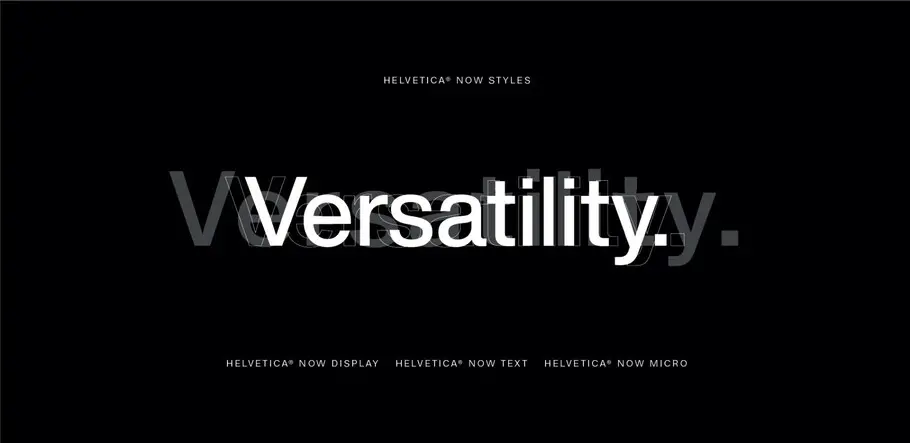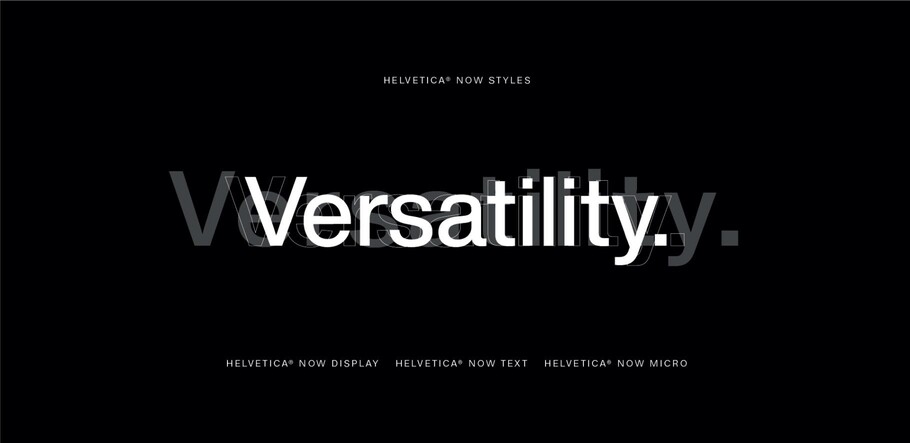
Was sind optische Größen und warum sind sie heute so wichtig?
Eine der jüngsten Neuheiten aus dem Monotype Studio, Helvetica® Now, bietet die drei optische Größen Mikro, Text und Display, wodurch sich die Einsatzmöglichkeiten von Helvetica dramatisch erweitern. Optische Größen waren zu Zeiten des Bleisatz praktisch Standard, gerieten aber in den ersten beiden Jahrzehnte des digitalen Schriftdesigns fast in Vergessenheit. So ist es kein Wunder, dass diese nützliche Technik selbst Designprofis kaum bekannt ist.
Situationsspezifische Typografie
Als „Optische Größen“ bezeichnet man im Typedesign die Praxis, Schriftzeichen für definierte Textgrößenbereiche unterschiedlich zu gestalten. Tatsächlich erleben wir eine Helvetica-Schlagzeile auf einem Großflächenplakat anders, als auf dem Smartphone oder in einer Zeitungsspalte. Die optische Anpassung einer Schrift für unterschiedliche Textgrößen kompensiert Wahrnehmungsunterschiede, zum Beispiel mit Änderungen beim Strichstärkenkontrast und beim Zeichenabstand. Lange Zeit war es üblich, Schriften in einer optischen Kompromissgröße zu entwerfen (Single Master) und zu hoffen, dass sie über alle Textgrößen gut lesbar funktioniert.
The optical sizes in Helvetia Now enable it to unction flawlessly in a range of applications, from large, eye-catching display text to hyper-legible micro type.
Bei der Neuveröffentlichung der klassischen Serif-Familie Walbaum fürs digitale Zeitalter, malte Monotypes Design Director Charles Nix folgendes Bild: „Stellen wir uns mal vor, dass die Proportionen 10-Jähriger als die perfekte menschliche Form definiert würden, und Babys wie verkleinerte Teenager aussähen und Erwachsene wie deren Vergrößerung. Babys sind aber zum Glück keine Miniaturen 10-Jähriger, und so sollte eine 5-Punkt-Schrift auch keine Verkleinerung einer 12-Punkt-Schrift sein.“
In der Zeit vor dem Type-Design am Computer passten die Schriftgestalter ihre Entwürfe für jede Größe einer Schrift an, um stets die beste Lesbarkeit zu erzielen. Kleinere Schriftgrade erforderten größere Buchstaben-Innenräume und mehr Zeichenabstand. Groß gesetzte Headlines dagegen profitieren von Buchstabenkontrast und -details. Als die ersten Schriften am Computer entstanden, setzte sich die praktische Single-Master-Methode, und One-Size-Fits-All wurde zur Norm.
Was ist normal?
Weil wir wissen, dass es die Größe für alles nicht gibt, überarbeiten und entwerfen immer mehr Schriftenhäuser ihre Fonts mit größenabhängigen Feinheiten, um die Makellosigkeit eines Text-Designs zu erhalten.
Obwohl es bei der Gestaltung und der Beurteilung von Schrift vor allem um deren Form(en) geht, bewege sich die Konzeption optischer Größen zwischen Kunst und Wissenschaft, betont Nix.
„Es erfordert nicht nur unsere Sensibilität für Formen und Zwischenräume“, sagt er. „Verbesserungen werden erst durch Beobachtung, Hypothesen und Experimente erreicht. Es geht um Studieren, Probieren und Verfeinern – ein iterativer Designprozess.“
Für Nix stehen ganz am Anfang Fragen: „Was ist eigentlich normal? Ich frage mich das jedes Mal, wenn ich eine Schrift mit optischen Größen entwerfe. Es klingt nach einer existenziellen Krise, denn Designs für sehr kleine Texte müssen den gleichen Eindruck wie bei normaler Textgröße ergeben. Und Entwürfe für größere Größen müssen das Normale so verfeinern, dass sie der Überprüfung durch eine Großaufnahme standhalten. Was ist normal? Es ist die Essenz dessen, was Design erreichen möchte – sein Ethos.“
Bei der Überarbeitung der Helvetica, einer vor über 60 Jahren veröffentlichten Familie, blieb das Monotype-Team der ursprünglichen Absicht treu: eine Schrift, die Klarheit, Einfachheit und Neutralität bietet. Das Ergebnis, Helvetica Now, ist eine für die heutigen Bedürfnisse angepasste Helvetica. Die Familie besteht aus 48 Schriften mit den drei optischen Größen Display, Text und Micro, die auf kleinen und großen Bildschirmen genau so überzeugen wie im Klein- und Großgedruckten. Oder wie Nix sagt: „Sie funktioniert einfach, in allen Anwendungsbereichen: von der überdimensionalen Fassadenwerbung in der City bis hin zum Mikrotext auf unseren Smartphones.“
Auch die Display-Schnitte, gedacht für Punktgrößen über 14, wurden neu gezeichnet, wobei die Feinheiten in den Buchstaben erhalten blieben und  deren Spationierung für Headlines optimiert wurde. Die Text-Version, gedacht für 8 bis 12 Punkt, wurde so optimiert, dass sie den Anforderungen an die Lesbarkeit von Mengentext gerecht wird. Die Striche sind robust, der Kontrast reduziert und die Abstände luftig, was zu einem angenehmen Lesen führt. Die Palette der Strichstärken erlaubt feinstes Informations- und Editorial-Design.
Die Mikro eignet sich für Kleingedrucktes zwischen 3 und 7 Punkt, sowohl auf Papier als auch für Retina-Screens. Die Lettern sind vereinfacht und übertrieben gestaltet, um das Gefühl von „Helvetica“ zu bewahren; der Zeichenabstand ist extrem großzügig – ein wesentliches Merkmal für hyperlesbare Mikrotexte.
Warum das wichtig für Marken ist
Optische Größen schaffen ein besseres Nutzererlebnis, erleichtern das Lesen und Verstehen und sorgen für Vielseitigkeit, Zugänglichkeit und Flexibilität. Dies ermöglicht es Marken, schnell und effektiv mit ihrem Publikum in einer unbegrenzten Bandbreite von Medien zu kommunizieren, ohne ihre visuelle Identität zu untergraben.
Vom Plakat bis hin zu In-App-Erlebnissen sind Stil und Lesbarkeit entscheidend. Markenbotschaften müssen in einem wettbewerbsintensiven Umfeld einwandfrei funktionieren. Jedes Hindernis für die Lesbarkeit oder Stilpatzer sind ein Zeichen gegen die Marke. Optische Größen funktionieren nicht nur besser, es sieht auch besser aus.